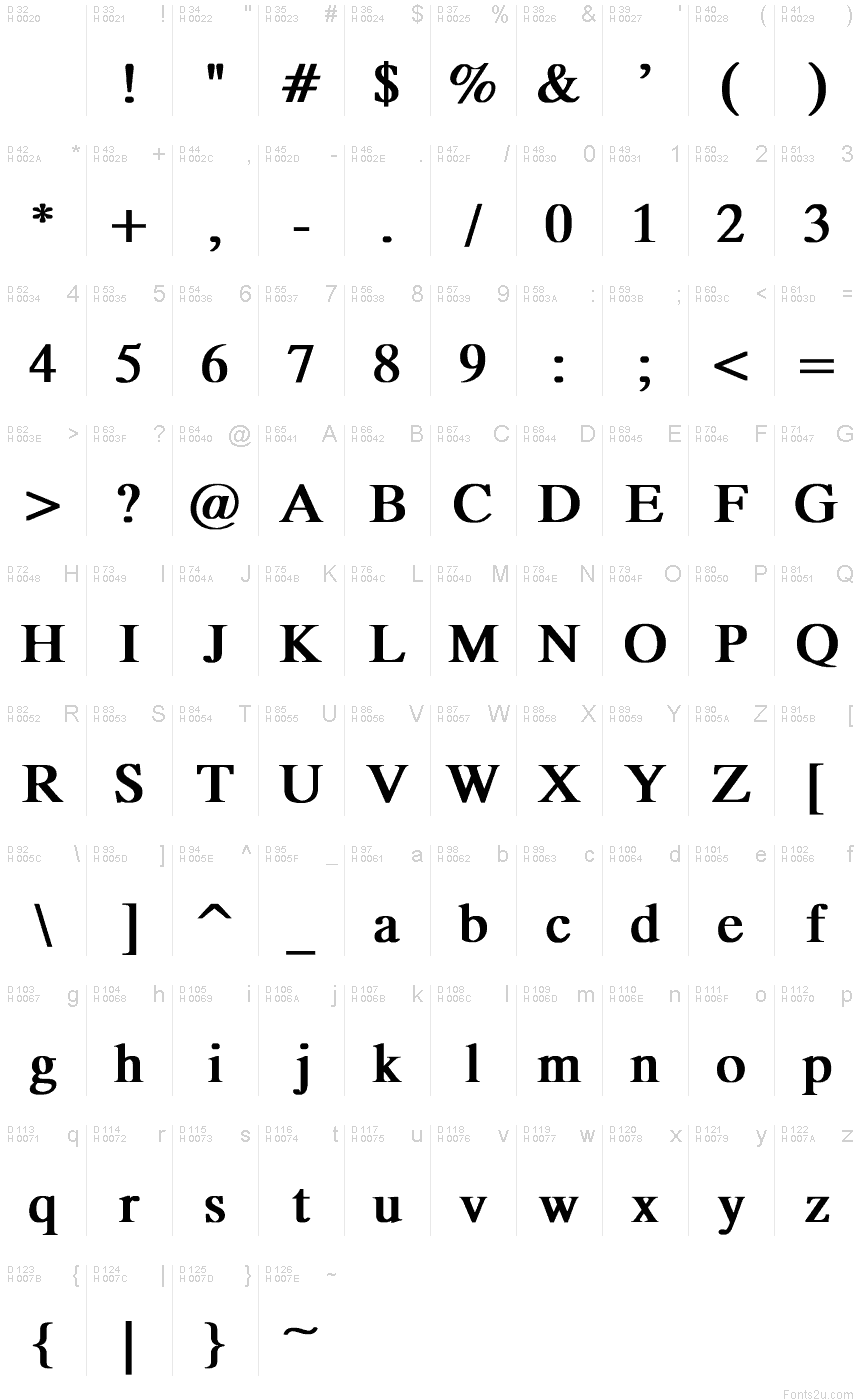
MicroTiempo Bold to darmowy krój szeryfowy z wyraźnymi, klinowymi szeryfami oraz kompaktowymi, zaokrąglonymi literami. Projekt przypomina klasyczny druk, z mocnymi pionami, płynnymi łukami i subtelnymi wykończeniami, co nadaje mu nieco formalny, wręcz książkowy charakter.
MicroTiempo Bold świetnie sprawdza się w nagłówkach redakcyjnych, na okładkach książek, w tytułach czasopism, logotypach i tekstach zaproszeń, ponieważ zachowuje swoją czytelność w dużych rozmiarach, nie sprawiając wrażenia przeładowanej. Ten darmowy font idealnie pasuje również do opakowań i marek stawiających na tradycję, gdzie klasyczne szeryfy dodają przekazowi stabilności i czytelności.